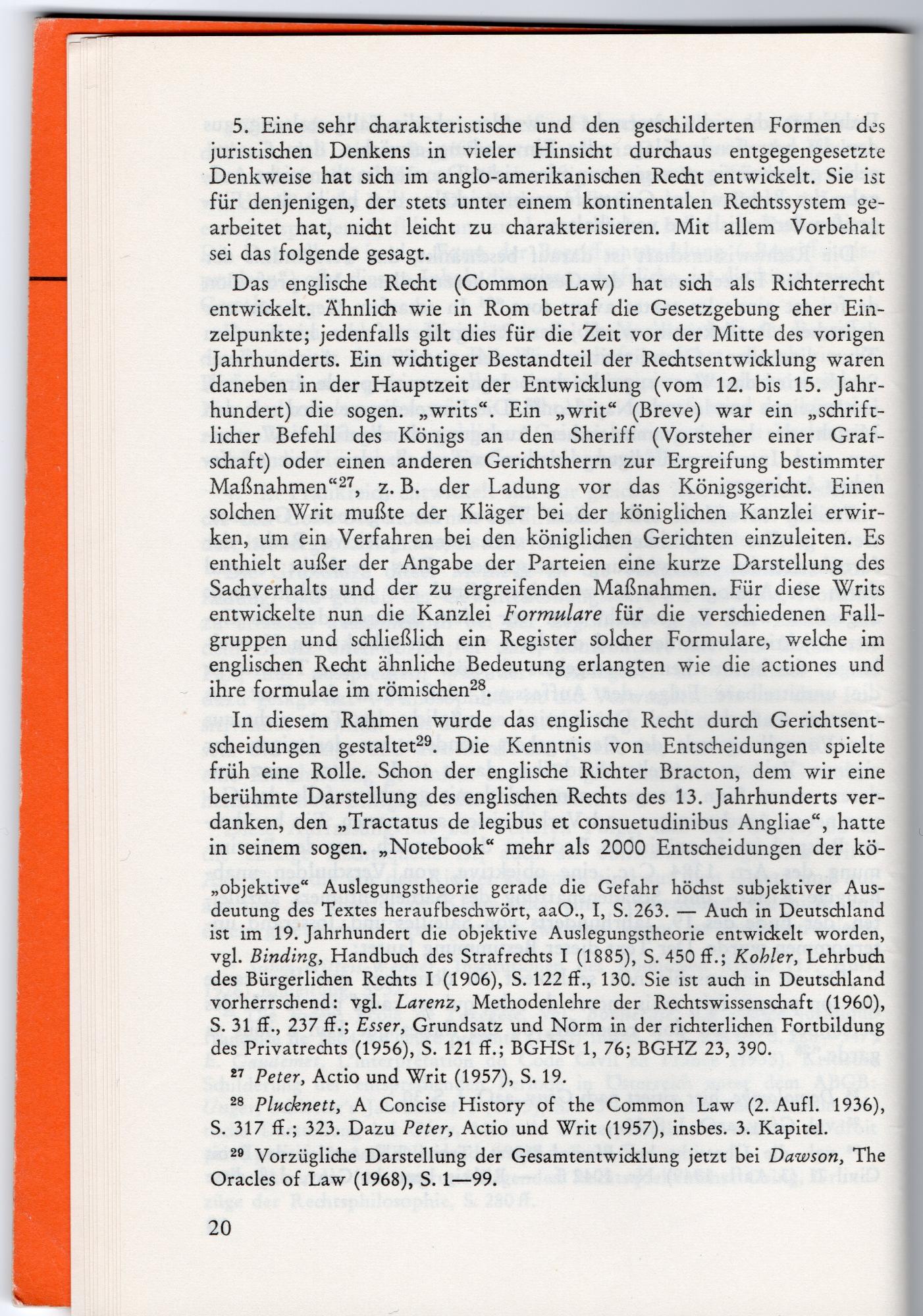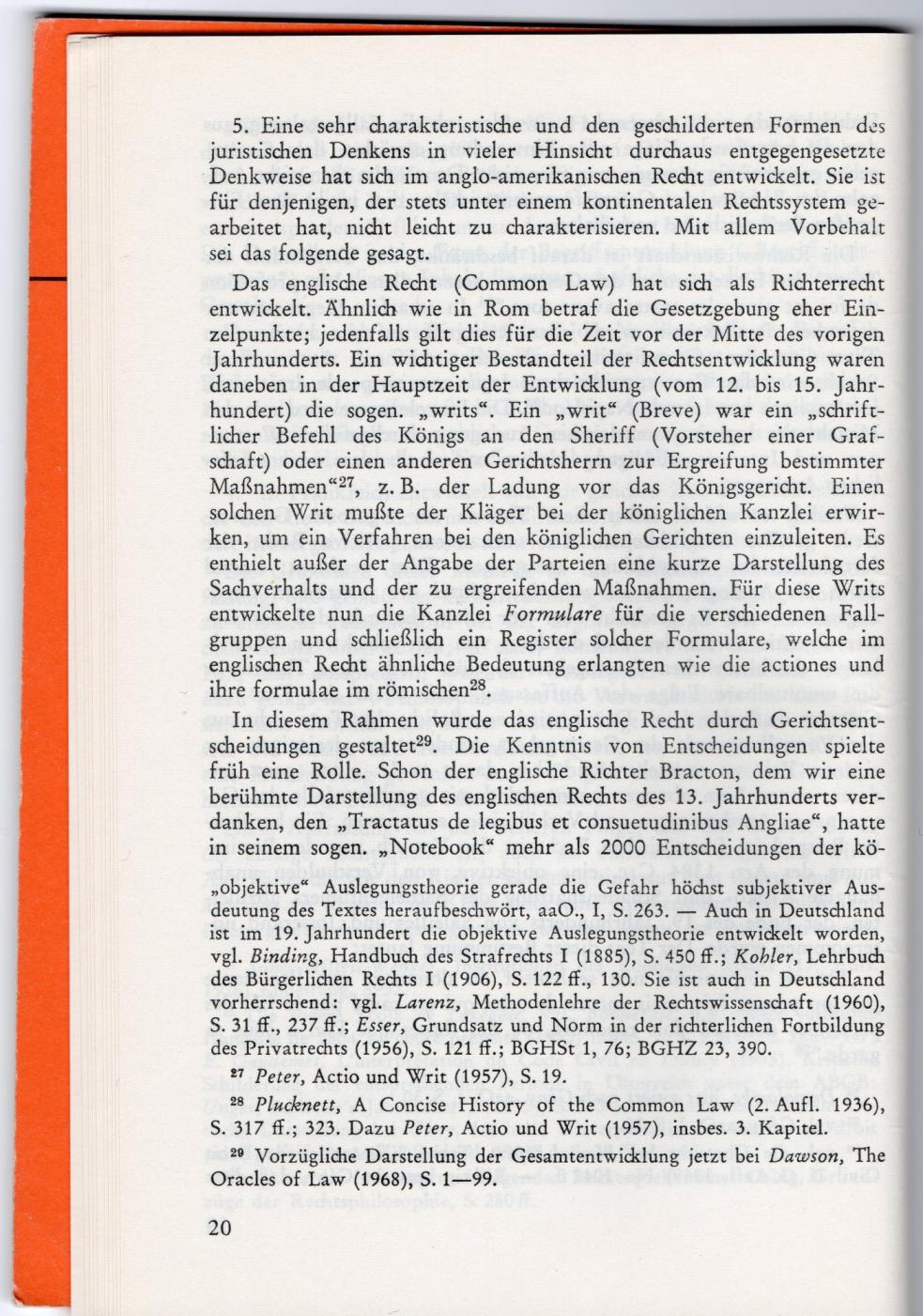
Schriftarten in Helmut Coing, Methodenlehre = Sammlung Göschen Band 4012, De Gruyter Verlag 1972
Kann mir jemand sagen, welche Schrift(en) in diesem Buch verwendet werden (Fließtext, S. 7 ff. des Buches, und insbesondere die Kursiven in den Fußnoten)?
Ist das Bleisatz? Gibt es diese Schriftart heute noch?
das sieht sehr nach folgendem aus: http://www.identifont.com/show?V7
Sabon
A descendant of the types of Claude Garamond.
One of a set of Equal width fonts with the font Sabon Bold.
Designer: Jan Tschichold
Year: 1964, 1989
Einer der Namen war IIRC auch classical Garamond? Schau einfach auch mal durch die Liste der ähnlichen Schriften.
Vielen Dank für die Antworten! Allerdings scheint mir, auch wenn ich nur ein typografischer Laie bin, die Sabon doch ganz andere Kursive Buchstaben zu haben (z. B. schauen "v" und "w" ganz anders aus, viel breiter)?
Gibt’s davon einen ordentlichen Scan? In dieser kleinen Textgröße wird die tatsächliche Schriftform durch die Scan-Einstellung doch schon mächtig verändert. Und Garamond-Schriften gibt es nun auch unzählige. Da müsste man schon eine perfekte Darstellung haben, um die Schrift zweifelsfrei zu identifizieren.
So richtig doll kann man die Details immer noch nicht erkennen. Sabon ist es aber definitiv nicht.
Auffällig finde ich ja das R mit dem kleinen Kopf :-? Ob das überhaupt eine geläufige Schrift ist …
Einiges scheint zu passen. Vielleicht wirkt das R durch Druck und Scan so eigenartig :-? Und es ist tatsächlich eine einfache Stempel Garamond.